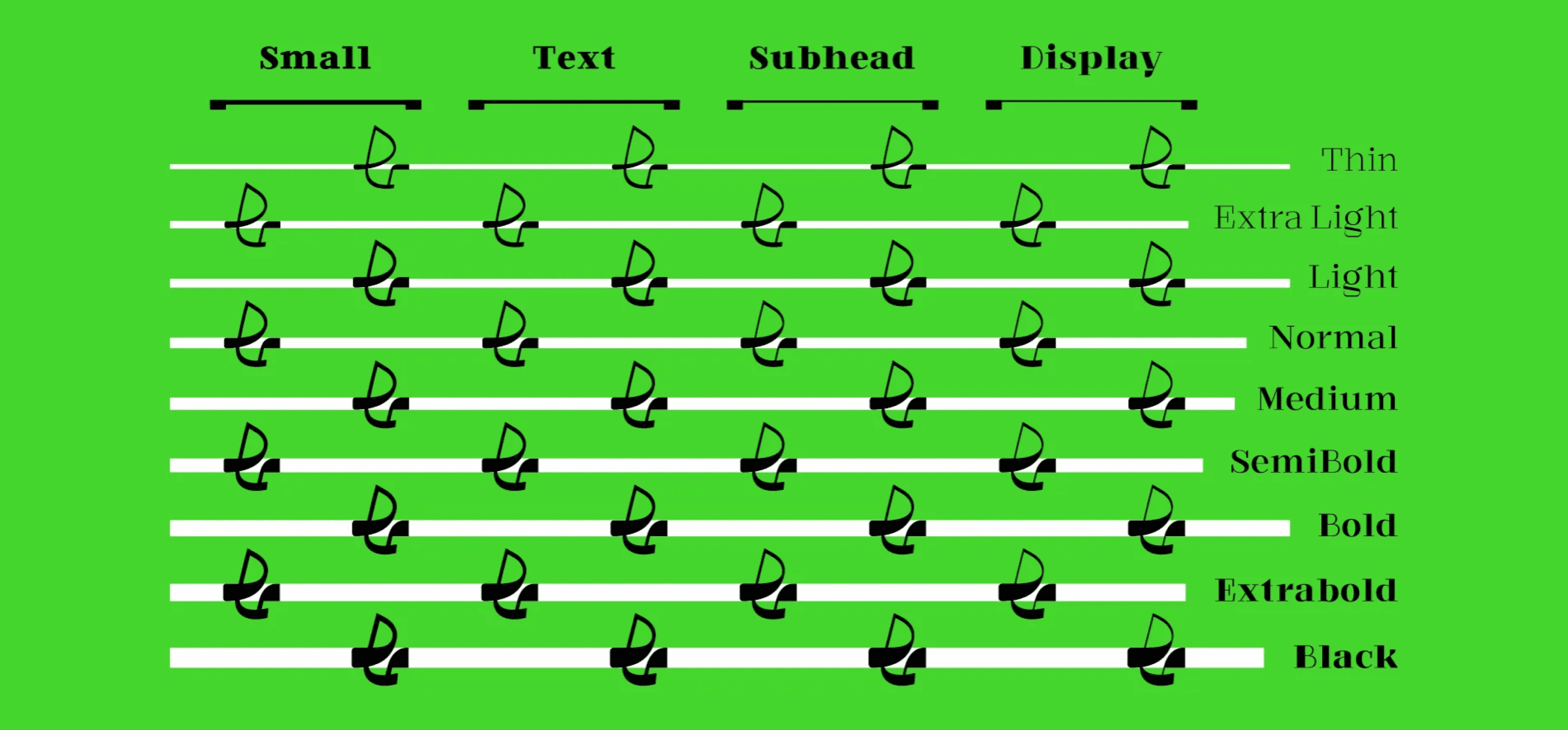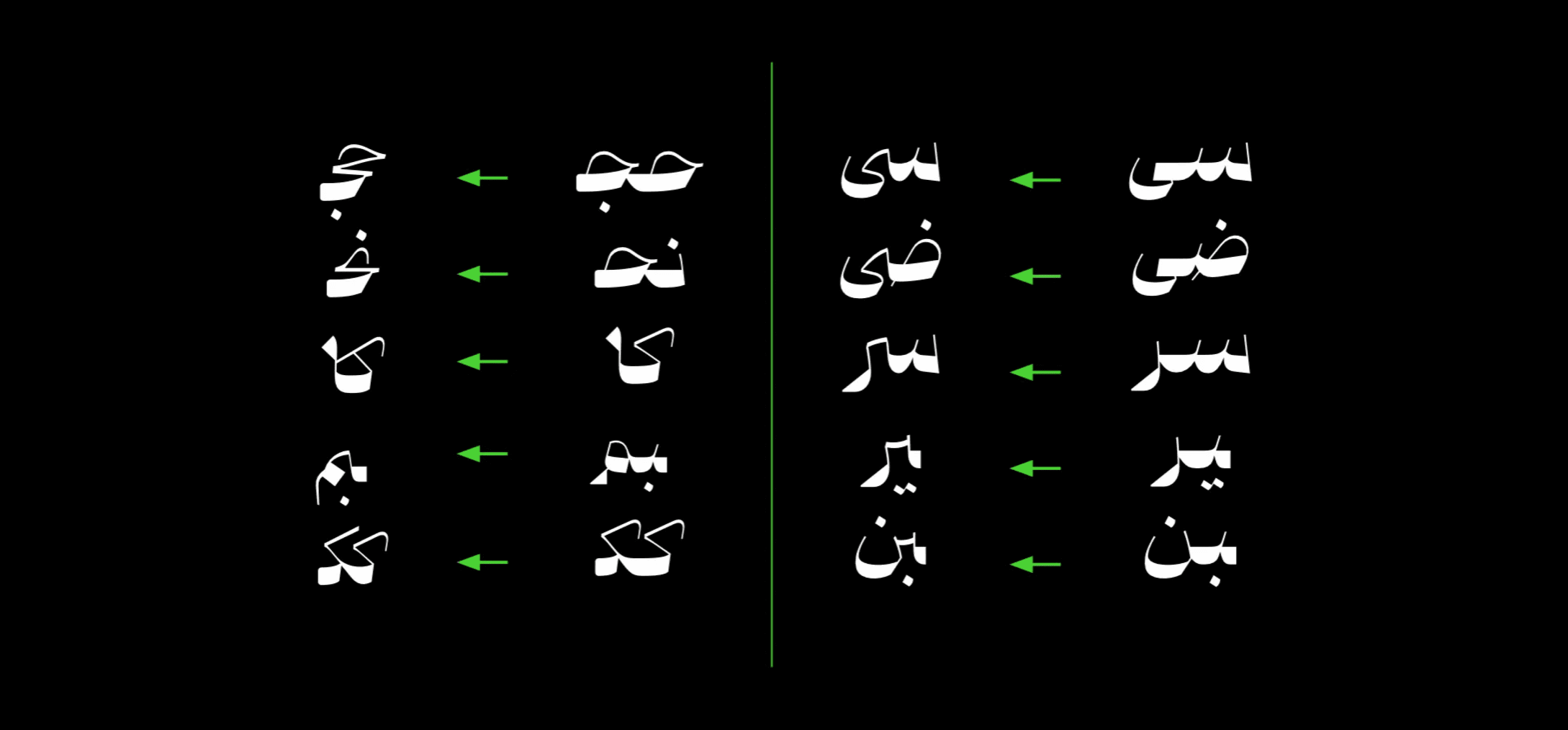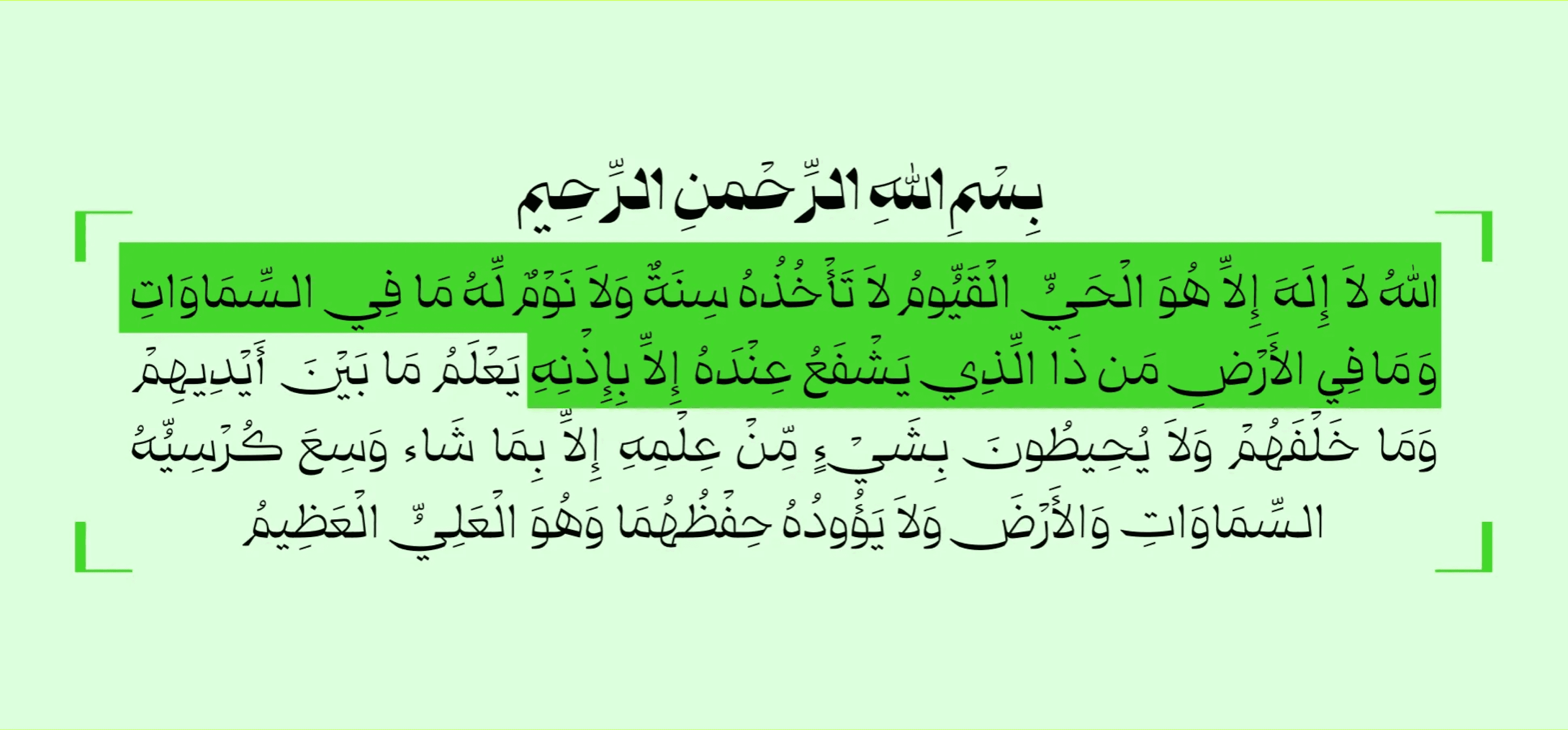
تم تطوير خط Quarantine خلال فترة الحجر الصحي الناتجة عن جائحة كوفيد-19 في ربيع عام 2021، واستمر تطويره وتوسيعه حتى صيف عام 2023.
ينتمي خط Quarantine إلى فئة الخطوط الزخرفية ذات النهايات المائلة (Display Serif)، وهو مثالي جدًا للتصاميم الإبداعية والنصوص القصيرة. وبفضل نبرته الجريئة وشخصيته المميزة، يبرز خط Quarantine بسهولة في أي مادة إعلانية أو ترويجية.
تم تطوير خط Quarantine خلال فترة الحجر الصحي الناتجة عن جائحة كوفيد-19 في ربيع عام 2021، واستمر تطويره وتوسيعه حتى صيف عام 2023.
ينتمي خط Quarantine إلى فئة الخطوط الزخرفية ذات النهايات المائلة (Display Serif)، وهو مثالي جدًا للتصاميم الإبداعية والنصوص القصيرة. وبفضل نبرته الجريئة وشخصيته المميزة، يبرز خط Quarantine بسهولة في أي مادة إعلانية أو ترويجية.
تم تطوير خط Quarantine خلال فترة الحجر الصحي الناتجة عن جائحة كوفيد-19 في ربيع عام 2021، واستمر تطويره وتوسيعه حتى صيف عام 2023.
ينتمي خط Quarantine إلى فئة الخطوط الزخرفية ذات النهايات المائلة (Display Serif)، وهو مثالي جدًا للتصاميم الإبداعية والنصوص القصيرة. وبفضل نبرته الجريئة وشخصيته المميزة، يبرز خط Quarantine بسهولة في أي مادة إعلانية أو ترويجية.